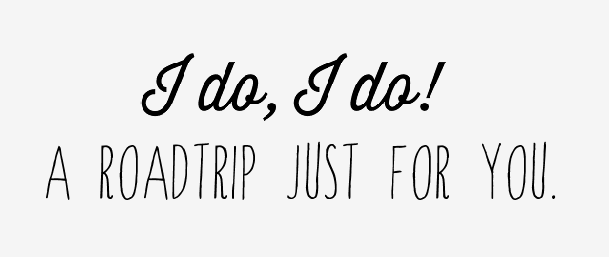
zeitgenössische condensed-Handschrift gesucht
ich bin auf der Suche nach der Handschrift in der Zeile unten, die sehr schmal läuft und zum oberen Font (das ist die Thirsty) passt. Bisher habe ich nur die Windsor Hand bei Dafont gefunden, aber die hat leider einen sehr beschränkten Zeichensatz.
Ich habe bereits ein dutzend Handschriften zum Vergleich eingesetzt (u.a die Paris, Taluhla, Berimbau, Mr Mustache, The Love Potion), aber keine hat denselben charmanten, leicht wackeligen Strich in Kombination mit der zarten Linie und den sehr schmalen Lettern.
Leider leider brauche ich aber Sonderzeichen. Und Kleinbuchstaben wären auch super. In der Windsor Hand sind diese aber nicht vorhanden. Hat jemand einen Tipp für eine sehr ähnliche Schrift oder dieselbe mit vollem Umfang?
Oder aber (zur Not) für eine andere Kombination, die ähnlich sympathisch wirkt?
Spontan fällt mir jetzt die LiebeErika ein :-?
Sie ist sicher eine gute Option, wenn sich nichts noch ähnlicheres findet.
Die Windsor Hand kommt mir aber noch eine Spur weniger nüchtern und damit freundlicher vor, weil sie nicht so geradlinig ist. Und sicher auch druch die minimalen Strichstärkenunterschiede, die den handgeschriebenen Charakter verstärken.
Verschiedene Schnitte wären auch ein großes Plus.
Hast du die Happy Cloud schon gesehen?
Die "Mr. Moustache" schießt mit ihren Kringeln leicht über das Ziel hinaus und wirkt seeeehr verspielt und die "Strangelove" ist eine Spur zu geradlinig.
Die "Happy Cloud" ist in der Anmutung ziemlich nah dran, nur sind die Oberlängen bei den Kleinbuchstaben leider recht ausufernd. Die "Pablo Skinny" ist zwar auch geradlinig, aber macht es mit dem auslaufenden Strich wieder wett (ich nehme an Tinte auf ungestrichenem Papier nachempfunden).
Und die "Ride my bike" könnte was sein. Wirklich cool ist auch, dass es so viele Schnitte gibt!